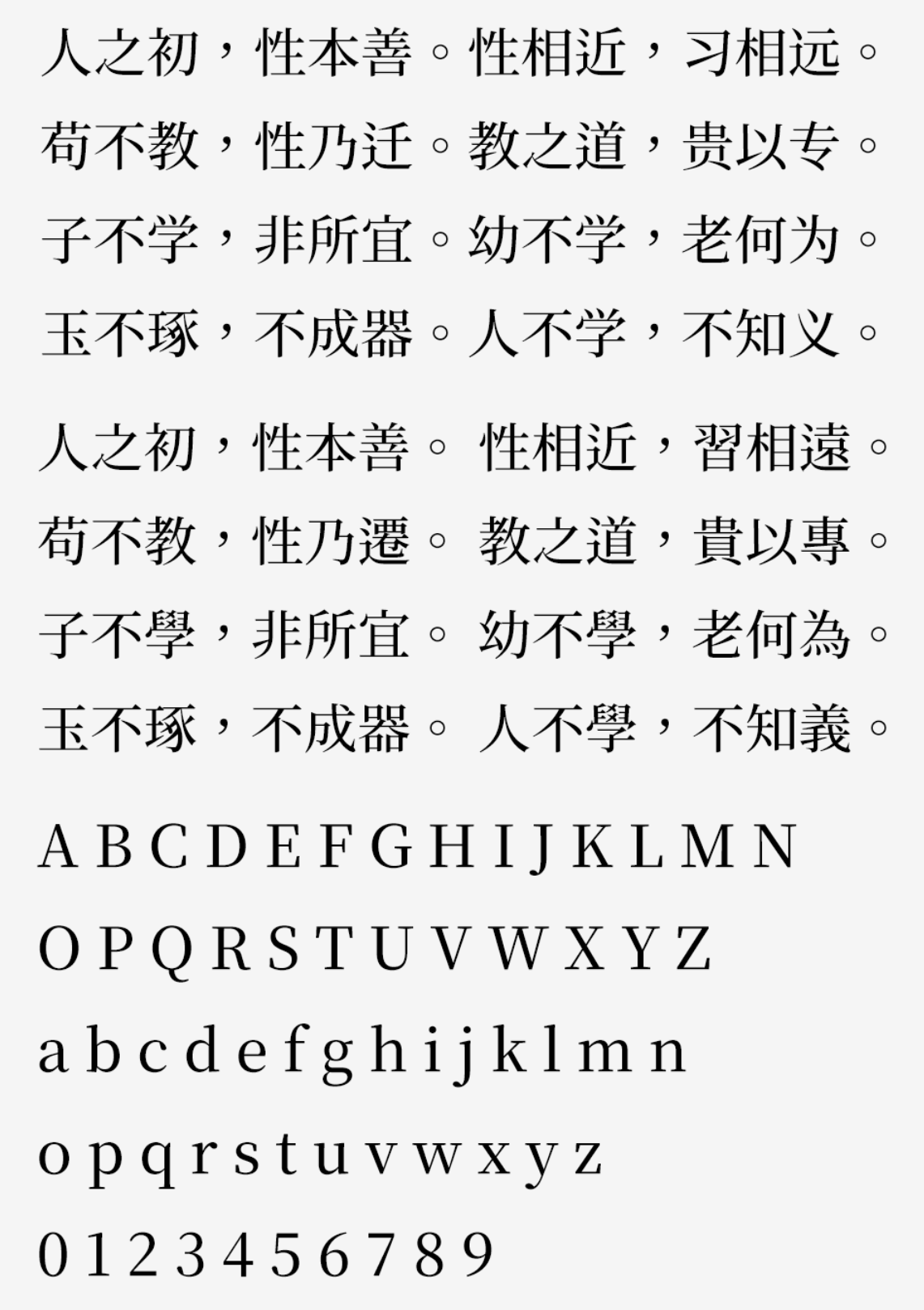
源样明体是基于思源宋体的开放原始码中文字体。采用思源宋体韩文(KR)版本的字符,配合繁体中文惯用的置中标点,可排版传统印刷体风格的文件。
传统印刷体:思源宋体预设的台湾版本(TW)采用教育部标准字体,虽然适合教育用途,但不尽符合传统印刷体审美观。例如点、挑、撇笔画太多,文件排列时的的跳动感较大。此项目采用KR版本的字符为主,较接近传统印刷体习惯,排列感较为整齐。
Note: 本项目并没有造新的字符,所有字符都是来自思源宋体本身。所以KR版本未收录的罕用字或简体字,仍然会是TW、CN风格。
汉字不缺字:保留思源宋体所支持之所有汉字(包或日、韩文汉字与简体字),一般会用到的汉字几乎不会有缺字问题。同时也保留了所有日文假名。(但删除了高达1万字的韩文字,有效降低字体档大小。)
Note: 本项目并没有造新的字符,简体字等当然会是CN风格。
标点符合繁体中文习惯:直接使用思源宋体KR版本排中文,会有标点置于左下的问题。此版本的标点符号仍采用繁体中文习惯,逗号、句号等都置于正中央。并且系统能正确识别为繁体中文字体。
另外,思源宋体的标点符号如「,」「。」设定有比例宽度的压缩字宽,在Illustrator、InDesign等环境下预设会压缩50%显示。这往往会让标点显得过窄。此版本移除了部分符号的压缩字宽信息,让这些标点符号字宽原则上保持全形。